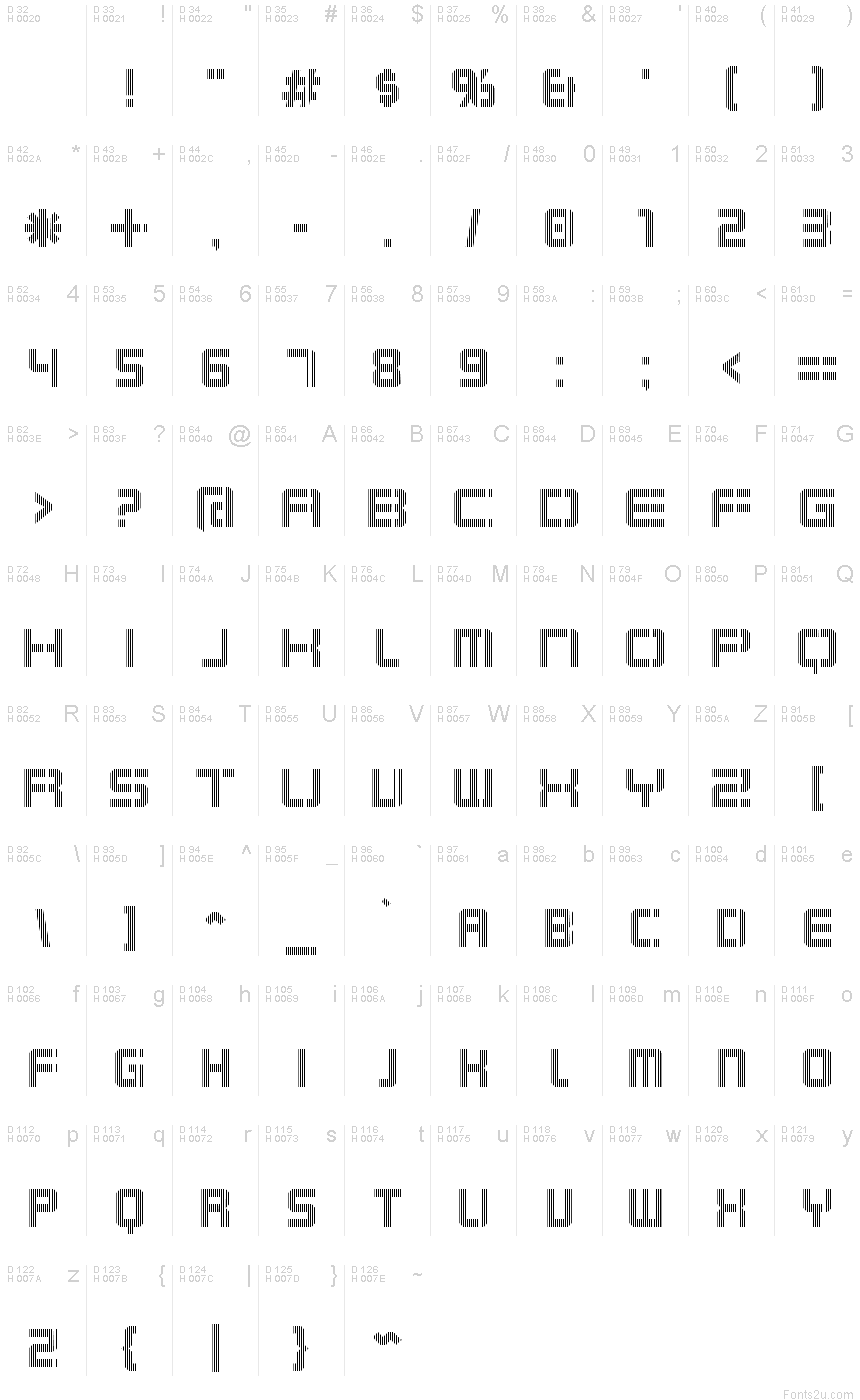
Karnivore Seven od Apostrophic Lab to darmowy techniczny krój typu display, który zamienia każdą literę w gęsty kod kreskowy z pionowych pasków. Znaki wyglądają, jakby zostały zeskanowane, poddane glitchowi i rozciągnięte, a gęste równoległe linie tworzą wibrujący efekt optyczny zarówno na ekranie, jak i w druku. Jest ostry, mechaniczny i nieco surowy – idealny, gdy szukasz kroju, który bardziej przypomina maszynę niż odręczne pismo.
Karnivore Seven pozwala nadać plakatom, ulotkom klubowym, identyfikacji wizualnej rave, eksperymentalnym okładkom albumów, tytułom sci-fi czy ekranom startowym gier pełny industrialny charakter. Ten darmowy font najlepiej sprawdza się w dużych rozmiarach, gdzie prążkowanie z daleka wygląda jak tekstura, a z bliska układa się w litery. W mniejszych tekstach połącz go z czystym, geometrycznym bezszeryfowym krojem, aby zachować czytelność, podczas gdy Karnivore Seven przejmie na siebie cały ciężar wizualny.
Karnivore Seven